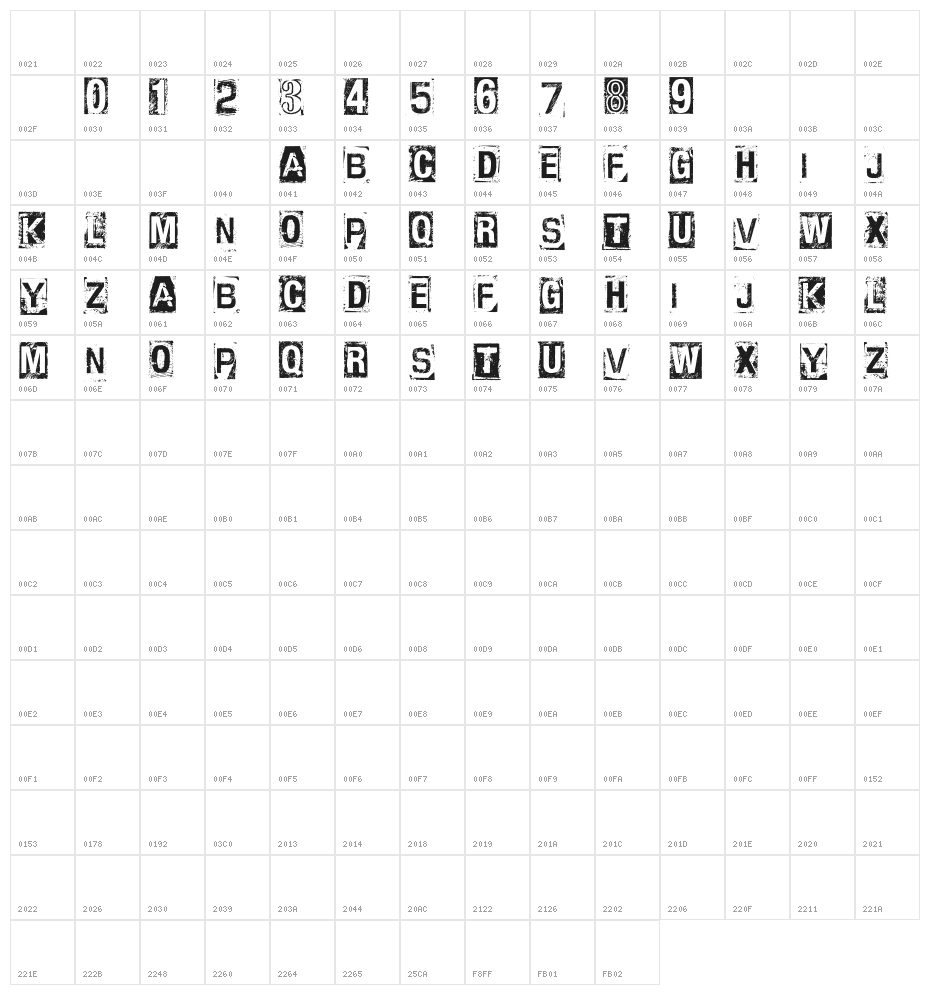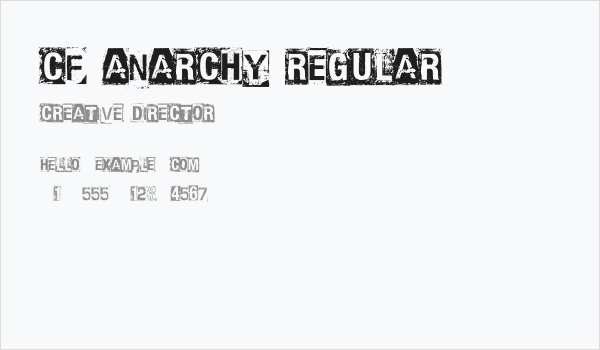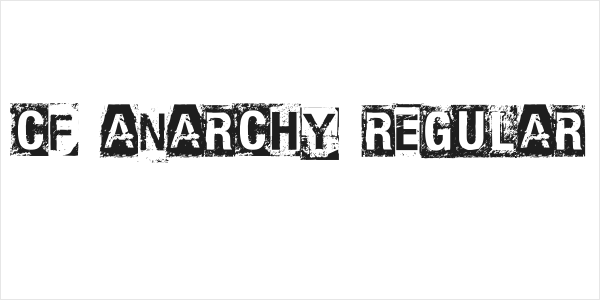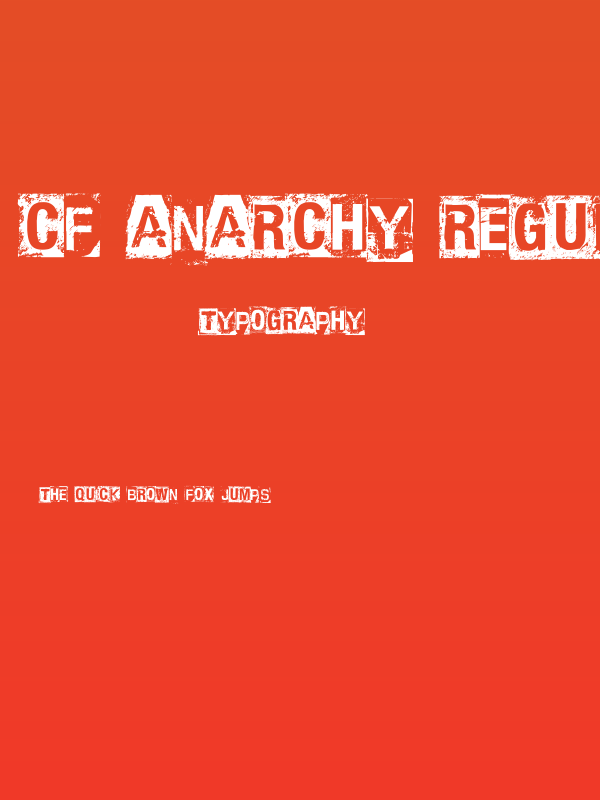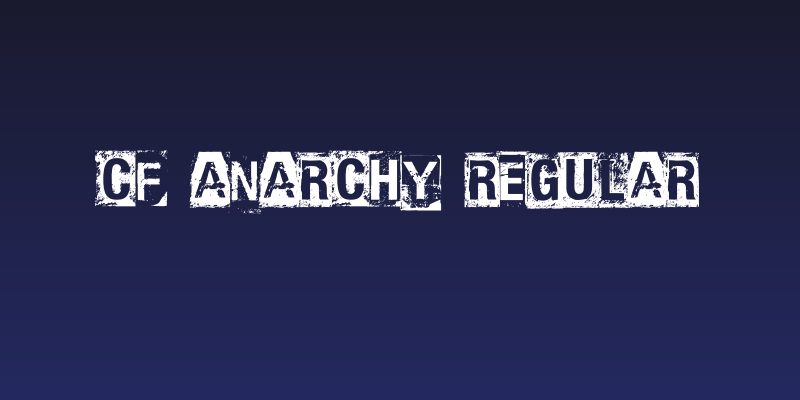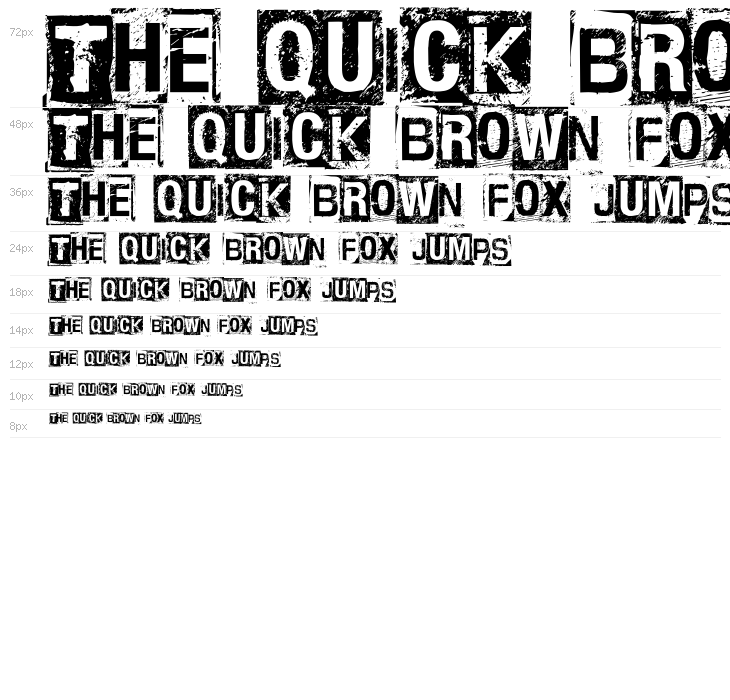
CF Anarchy Regular Font
| Categorie | Messy |
| Stile generale | Grunge, Urban, Edgy |
| Caso d'uso | Headlines, Posters, Branding |
| Progetti proposti | Ideal for music album covers, posters, streetwear branding, and any design needing a bold, urban edge. |